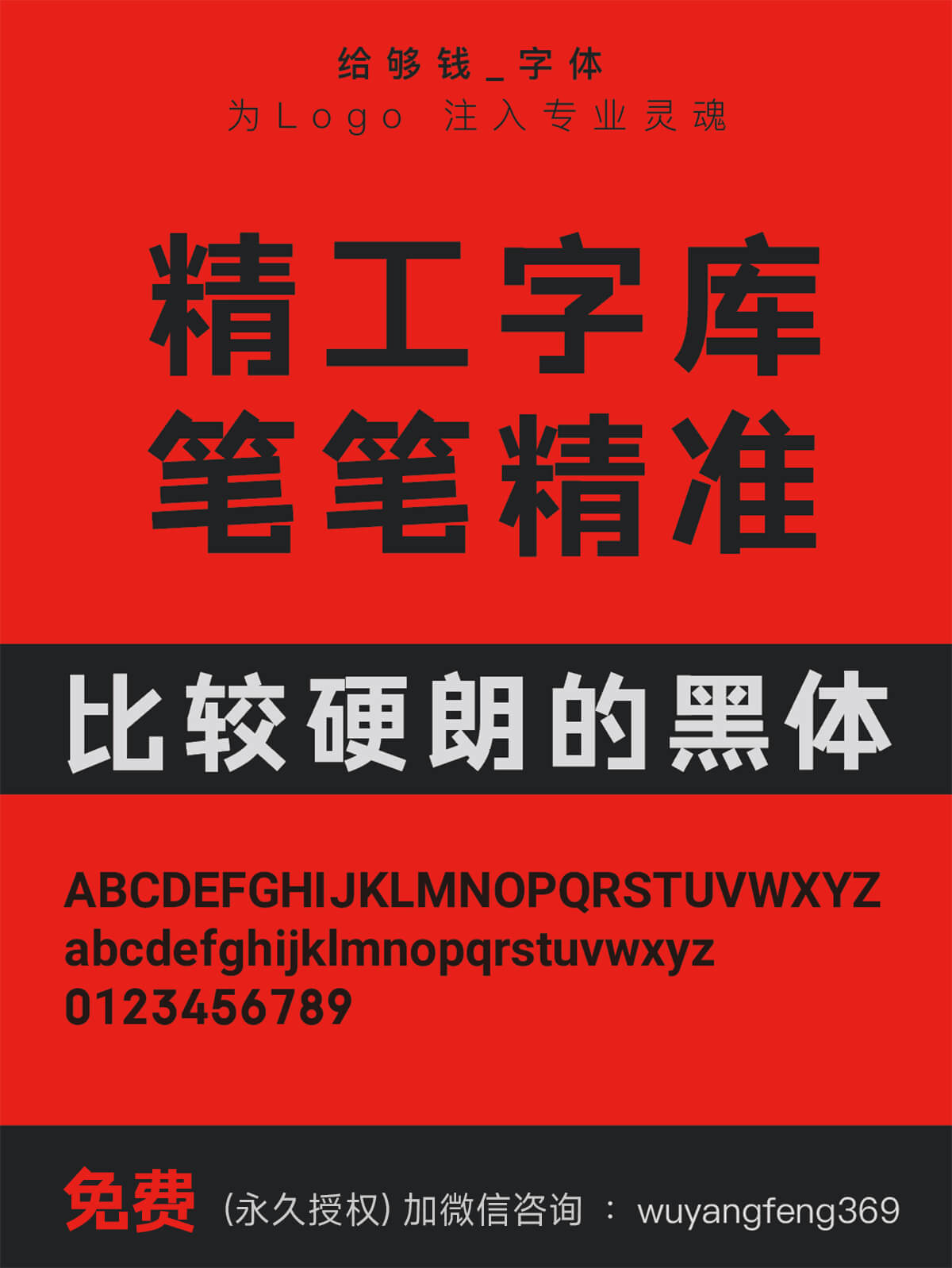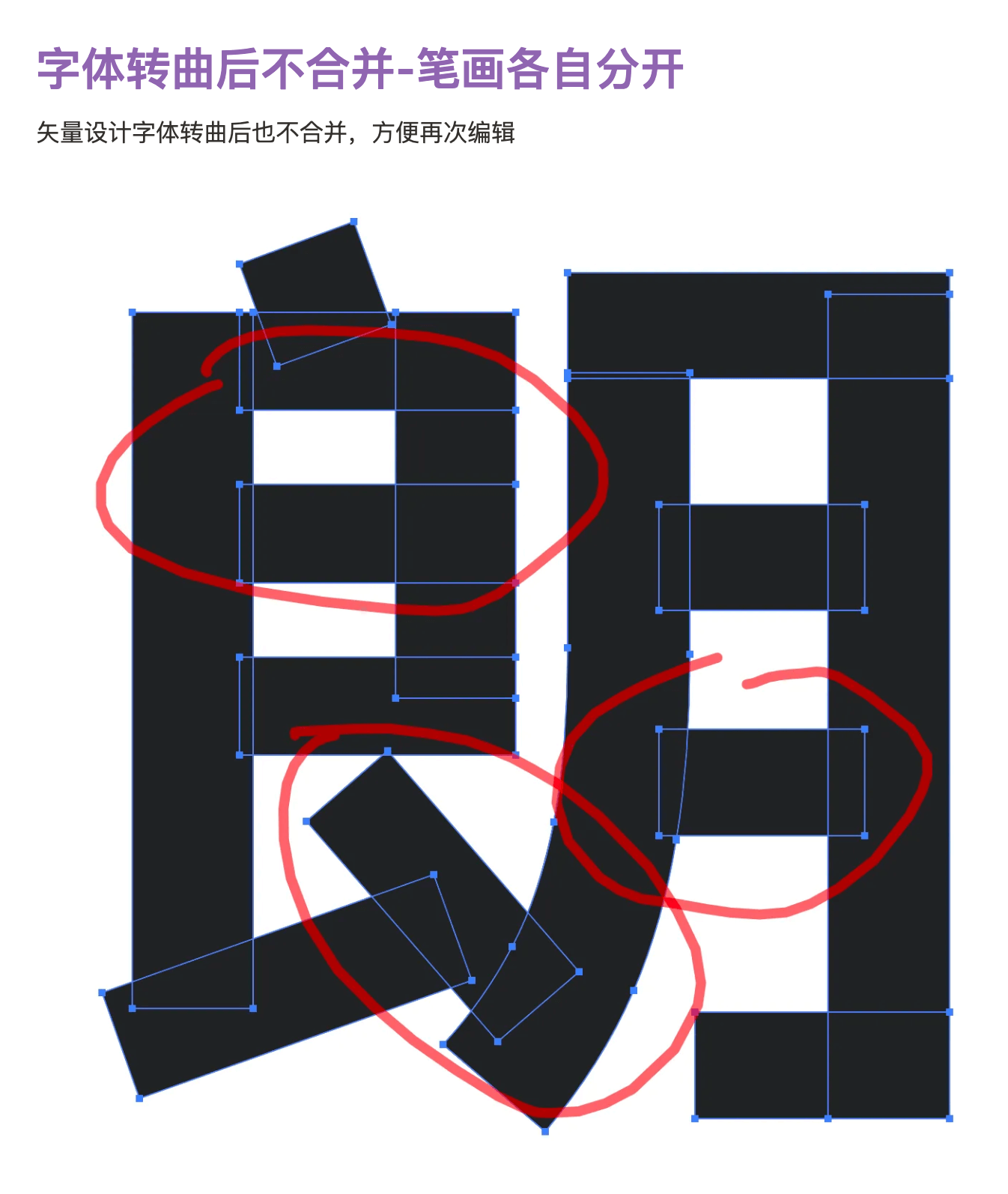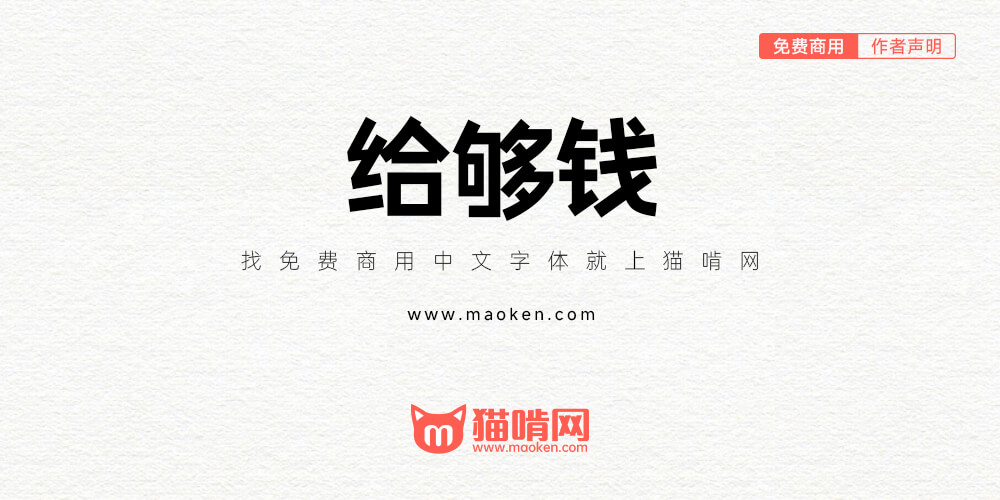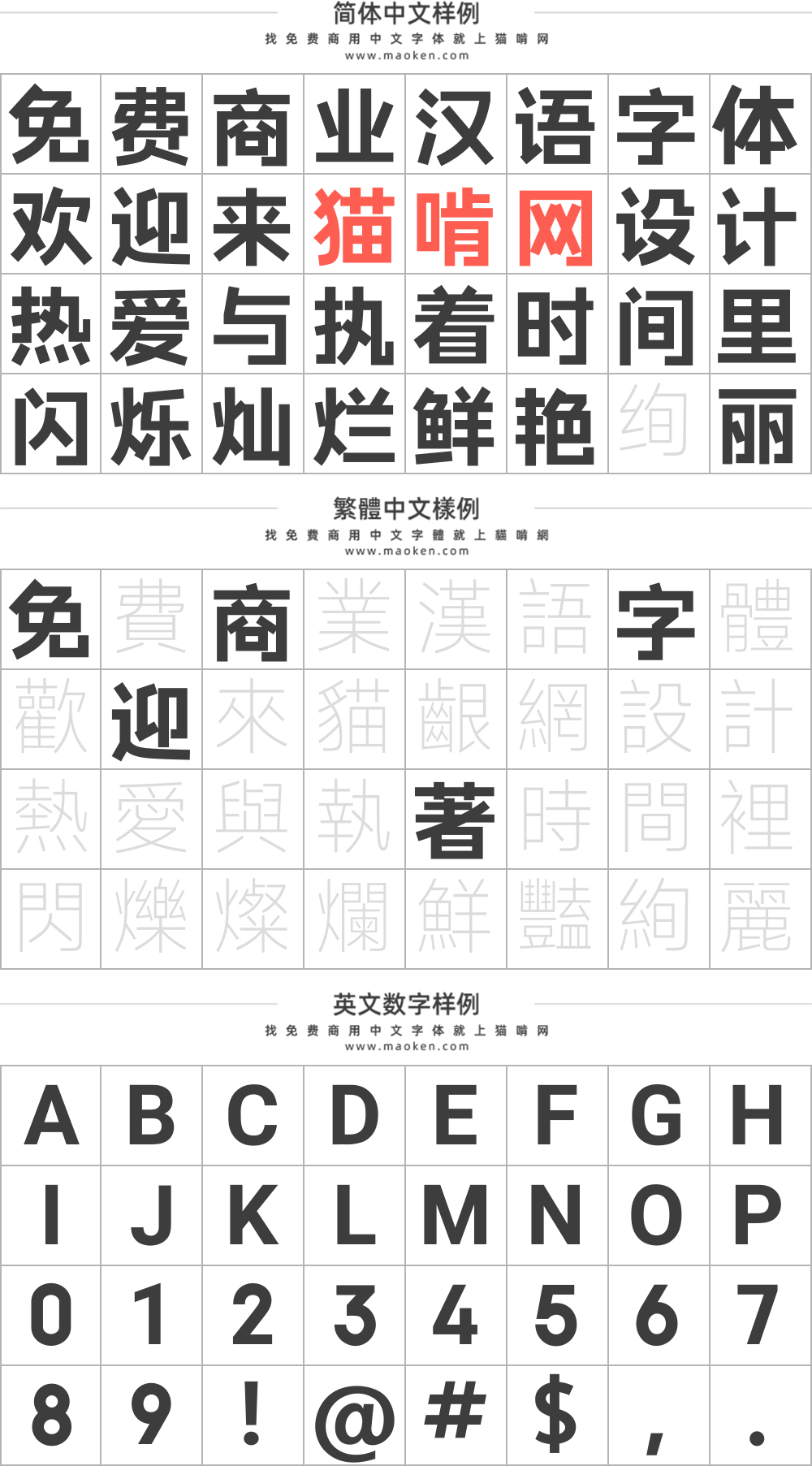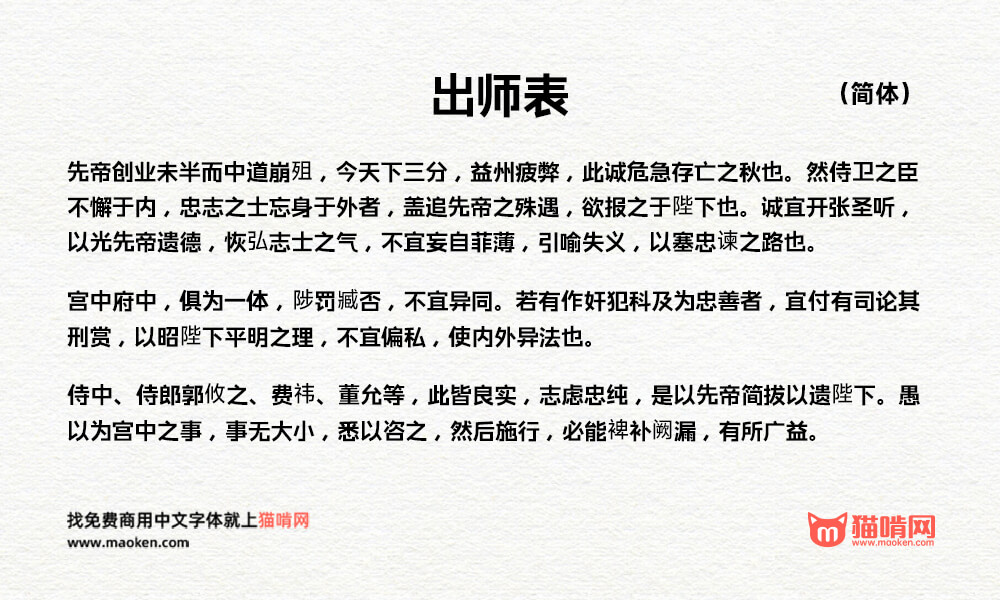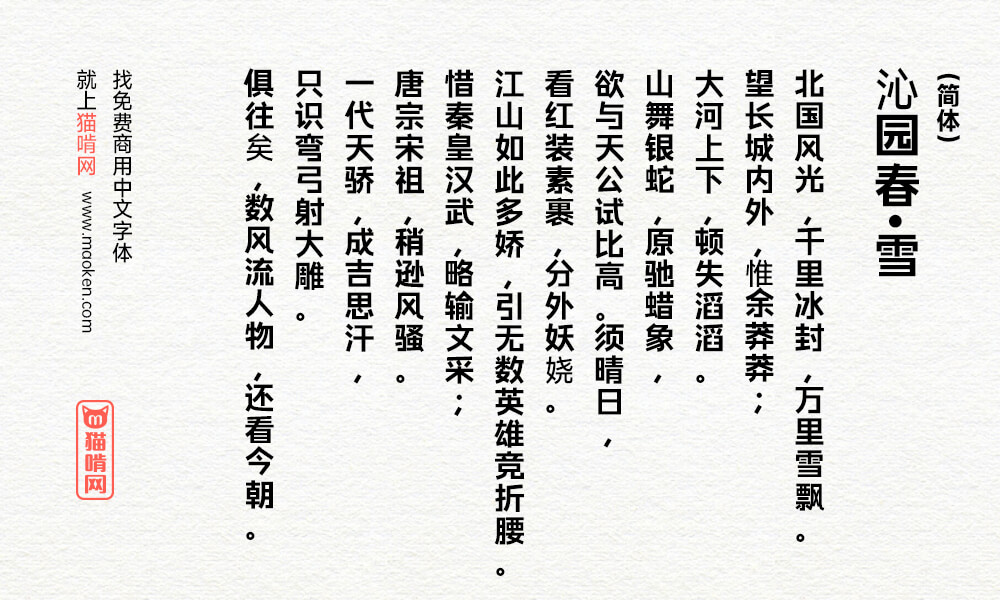
给够钱:吴杨峰出品比较硬朗的黑体 开放永久免费商用
字体作者:吴杨峰 (中国大陆) 字体字重:1个
给够钱体是吴杨峰出品比较硬朗的黑体,之前售价199元,现在吴杨峰决定把这款字体开放永久免费商用并委托猫啃网进行进行发布。
• 更新版本,版本号没有变,中英文略微调整了。
• 字体更新了新的对齐方式,更美观。
• 给够钱字体发布。
好看
没人觉得 这字体跟mit授权的日本小夏黑体风格很像吗
方方先锋体平替(bushi
• 不不不,跟先锋细节完全不同,先锋太刻意都直,这个更方正,直但不呆板
这款字体霸气豪横,笔画简洁硬朗!这款字体你不会看到各种角度的斜角的收笔,正直、硬朗、结实!
嗯,不喜欢低于90度的尖角或转角,也不喜欢太多圆角,太柔,能直全直,即便不得以使用弧形也要硬朗的弧
非常好看的字体,很正,很方正,非常喜欢
这款字体只包含《现代汉语常用字表》3500 字。
• “洱”字也没有
This font’ s Alphabets arpe from Rodoto….
• Roboto 2.x is distributed under Apache license, so it is not necessary for modified versions to be opensource.
• does anyone know where the numerics are from?
• 有眼光,数字集合三款字体而成,